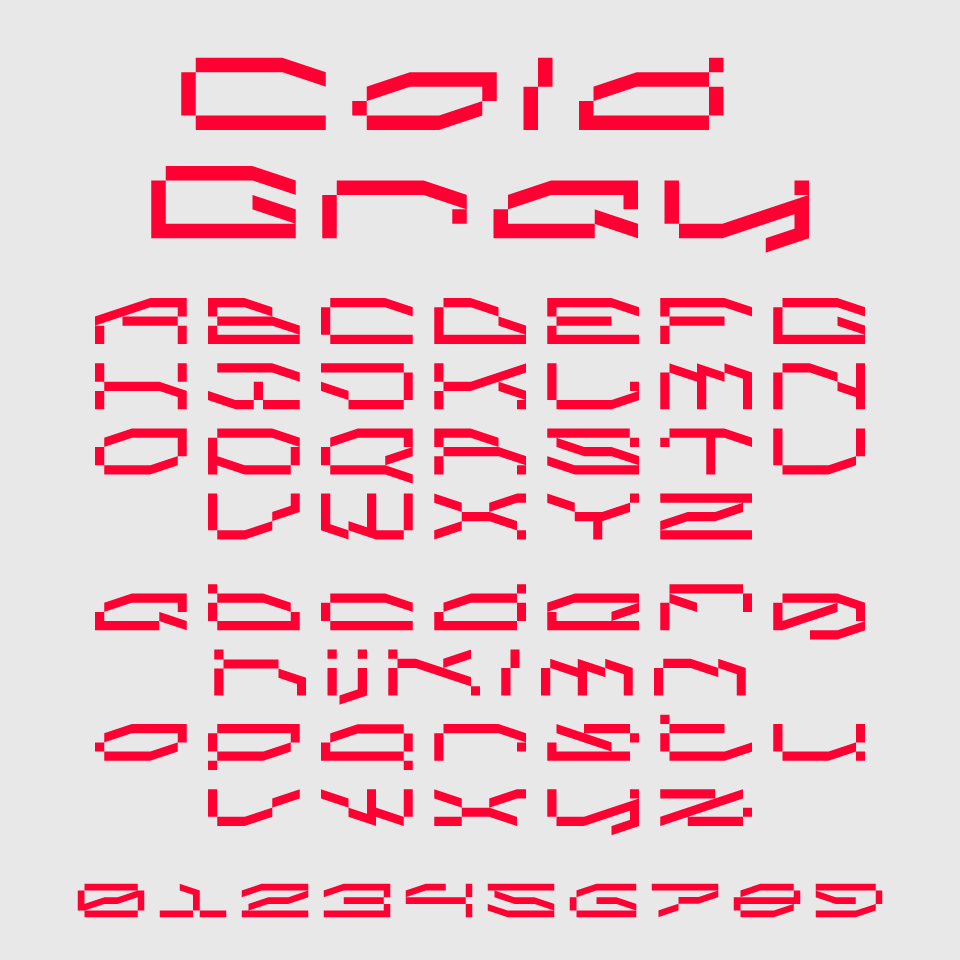
Cold Gray フォントは、無機質でブロック状の構造が特徴的な、未来感を感じさせるフォントです。
文字は直線と鋭角で構成されており、まるでコンピュータの基板や、デジタル都市のサインを思わせるようなデザインです。グリッド状に整った文字列が、人工知能やデジタル感の世界観を呼び起こします。
すべての文字が幾何学的なルールに基づいて設計されており、無駄のない造形に研ぎ澄まされた雰囲気があるカッコいいデザインとなっています。